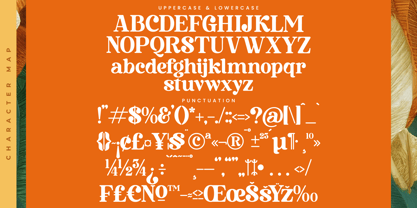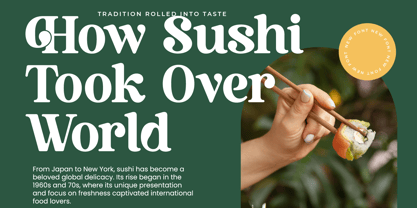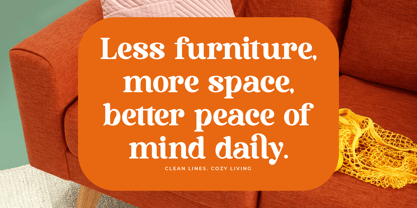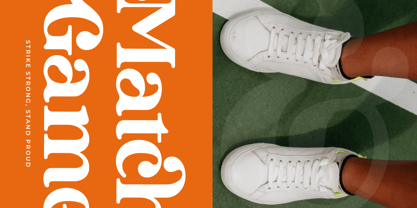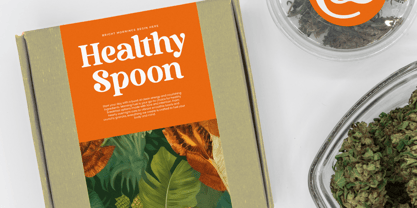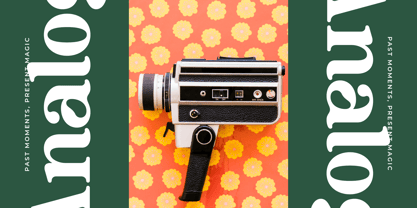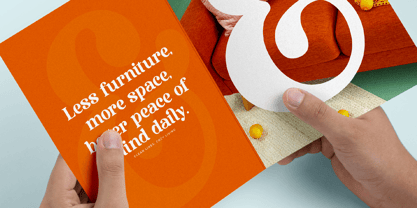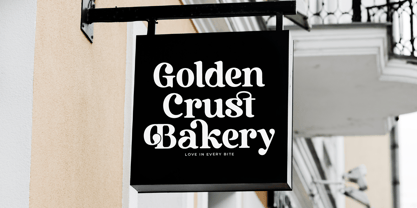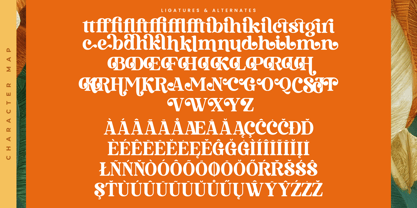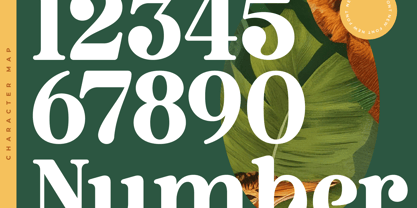
Bruge Vibes
por Timelesstype Studio
La familia tipográfica Bruge Vibes fue diseñada por Heru Utama Putra y publicada por Timelesstype Studio. Bruge Vibes contiene 2 estilos y opciones de paquete familiar.
Bruge Vibes - Bold Alternate Serif Font , from Timelesstype, Suitable for any projects such as: logos, branding projects, homeware designs, product packaging, mugs, quotes, posters, shopping bags, t-shirts, book covers, name card, invitation cards, greeting cards, label, photography, watermark, special events, and all your other luxury and beautiful projects that need a Luxury Serif taste.